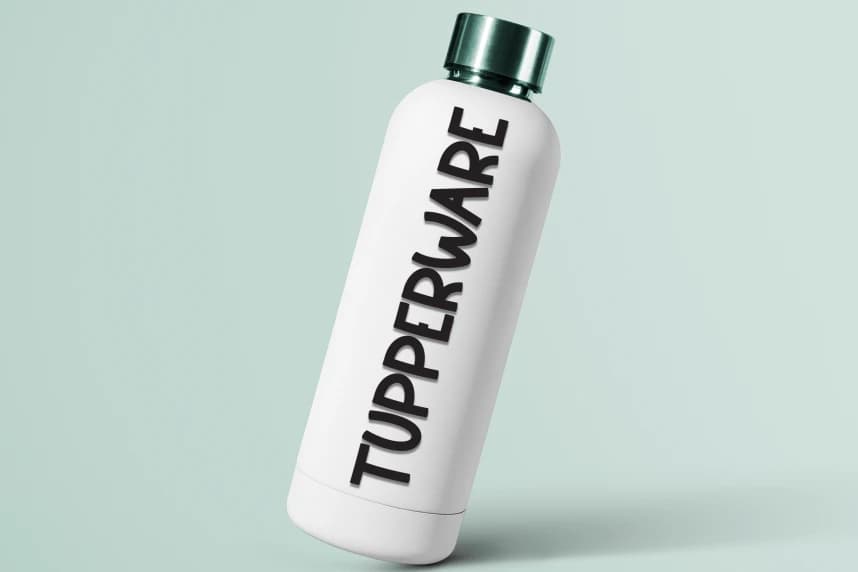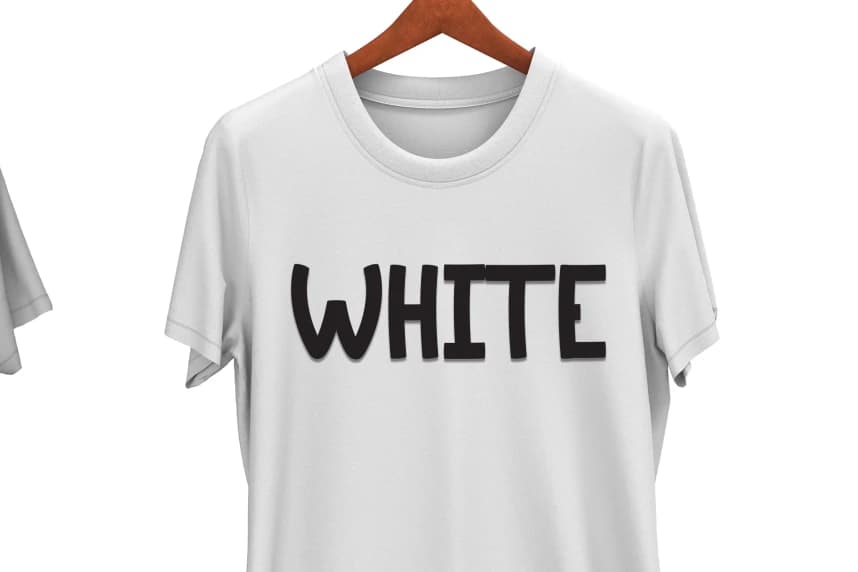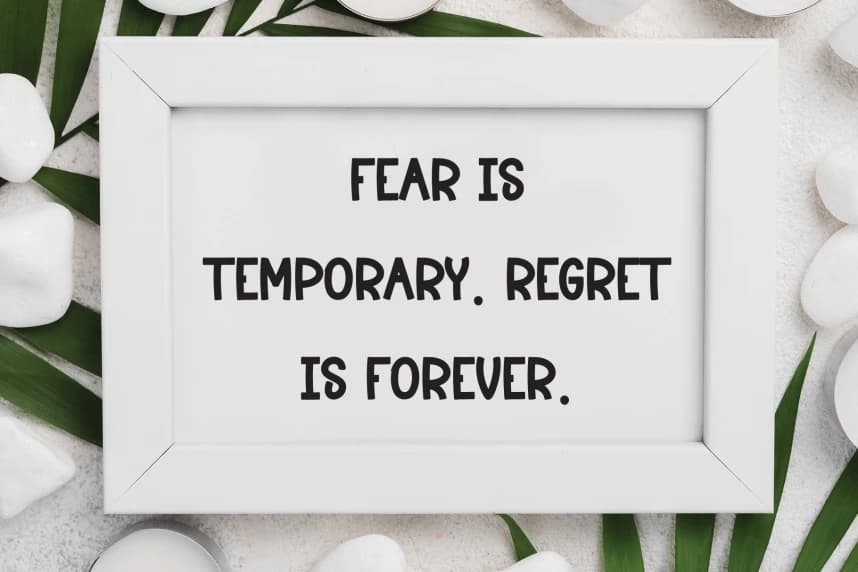
Cooking Morning Neşeli Yazı Tipi
Cooking Morning Playful Font, tatlı ve samimi bir el yazısı görünümlü yazı tipidir. Sevimli ve eğlenceli olan bu yazı tipi, düğün davetiyelerini ve kartları yazmak için veya eğlenceli bir dokunuşa ihtiyaç duyabilecek diğer tasarımlar için idealdir!
Cooking Morning Playful Font, tatlı ve dost canlısı bir el yazısı gösterim yazı tipidir. Sevimli ve eğlenceli, bu yazı tipi düğün davetiyelerini, kartları yazmak için veya oyuncu bir dokunuşa ihtiyaç duyabilecek herhangi bir tasarım için idealdir!